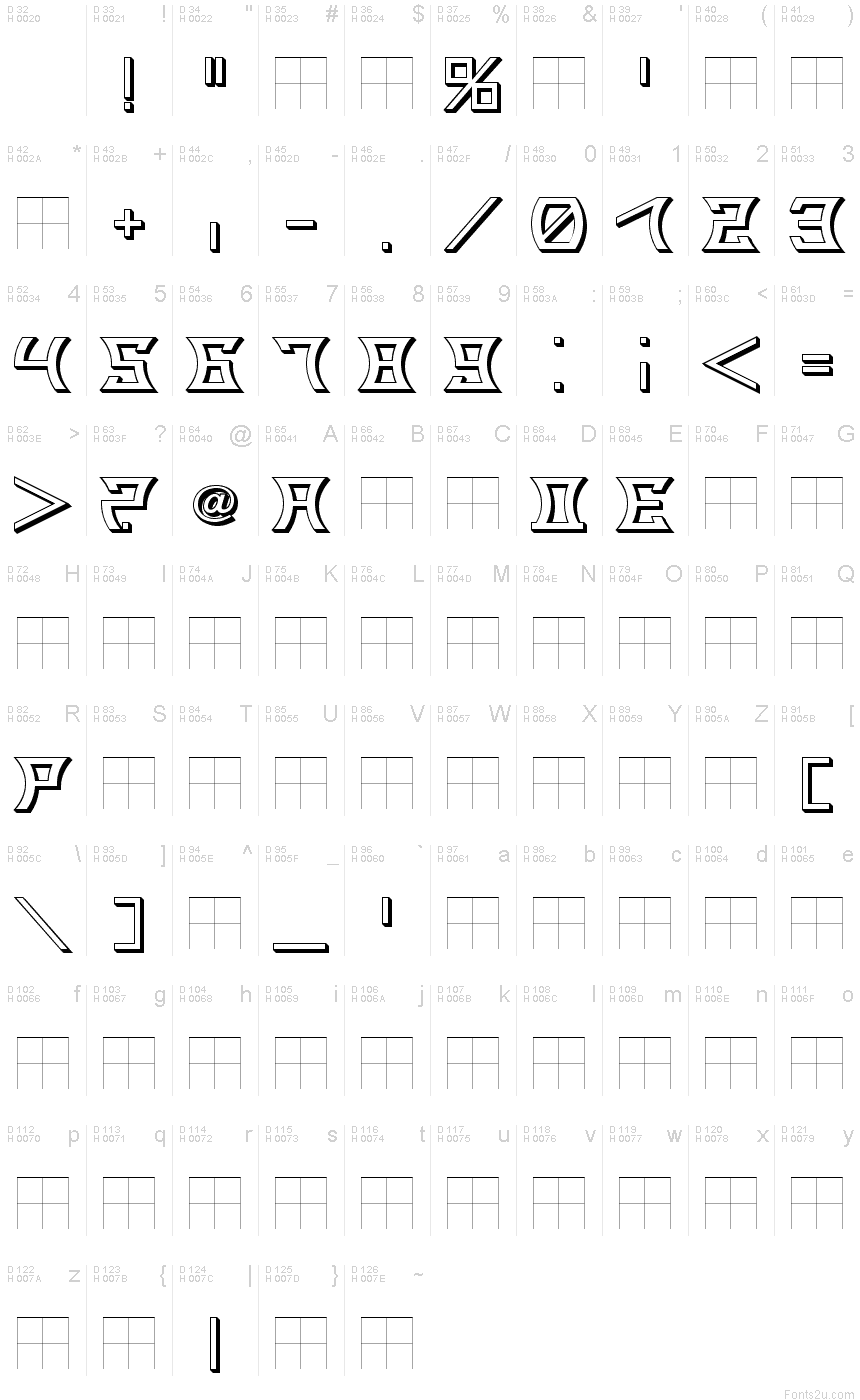
Rade 20 von Nikola Kovanovic ist eine kostenlose Tuscan-Display-Schrift mit der dramatischen Ausstrahlung alter Poster. Die Buchstaben setzen auf breite, gebrückte Serifen und eingezogene Innenformen, während die abgerundeten äußeren Kurven und kleinen, kronenartigen Einkerbungen für einen geschnitzten, ornamentalen Rhythmus sorgen.
Sie eignet sich perfekt für Plakate, Buchcover, Musik-Flyer, Titelkarten und Logo-Schriftzüge, bei denen wenige Buchstaben den Ton angeben sollen. Als kostenlose Schrift ist sie zudem ideal für Monogramme, Verpackungsdesigns und kurze redaktionelle Akzente – besonders, wenn man diesen Vintage-Charme von Jahrmärkten oder Saloons sucht, ohne dabei überladen zu wirken.